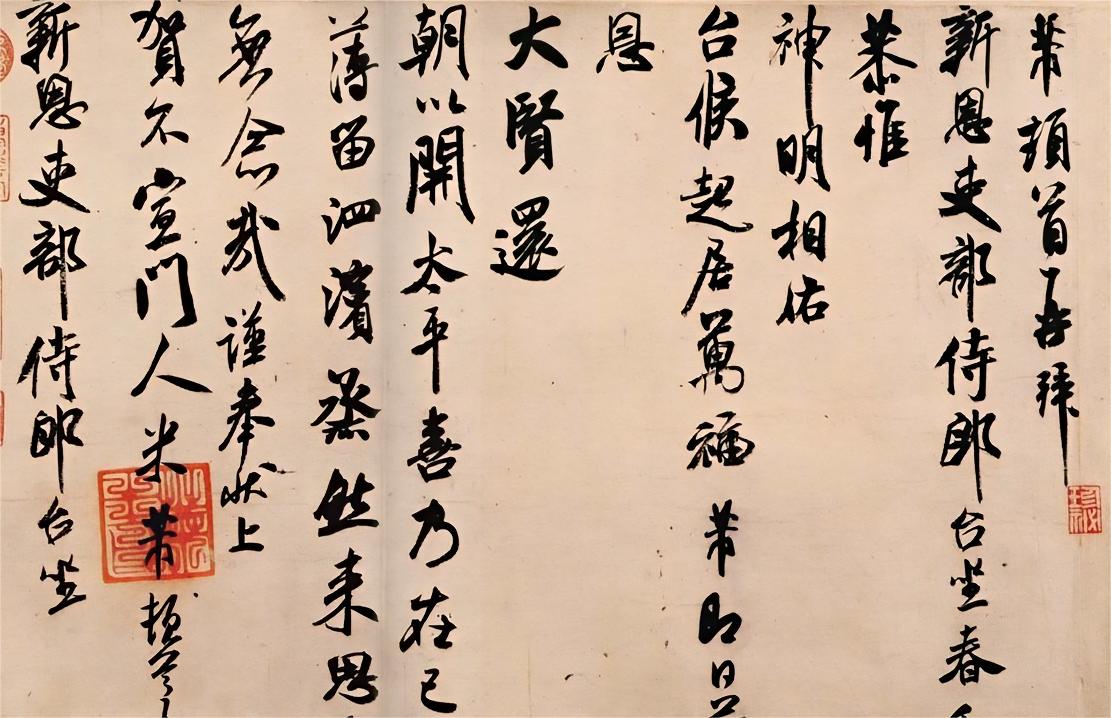
字体全名: 汉标米芾行书新恩帖
字体简介: 下载须知:本字库非标准GB2312字库。本字库只包含了米芾《新恩帖》真迹上的“102个字”。米芾行书尺牍欣赏《新恩帖》纸本,纵33.3厘米,横48.5厘米。北京故宫博物院藏。《新恩帖》是给一位新任吏部侍郎的贺信。系米芾50岁后的晚期作品,神完气足,炉火纯青,个人风格已十分成熟。